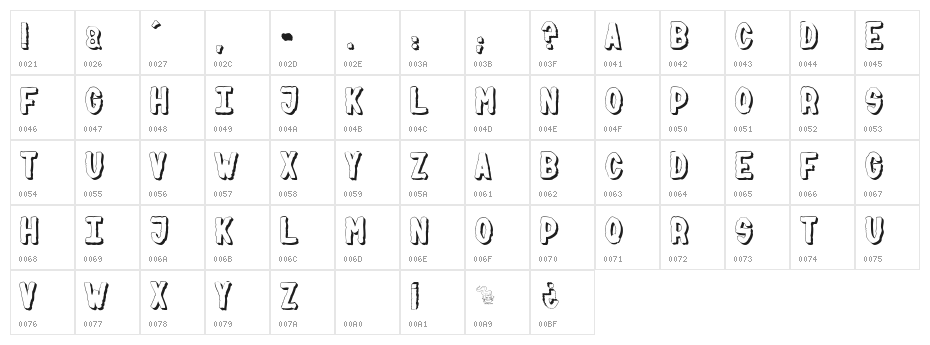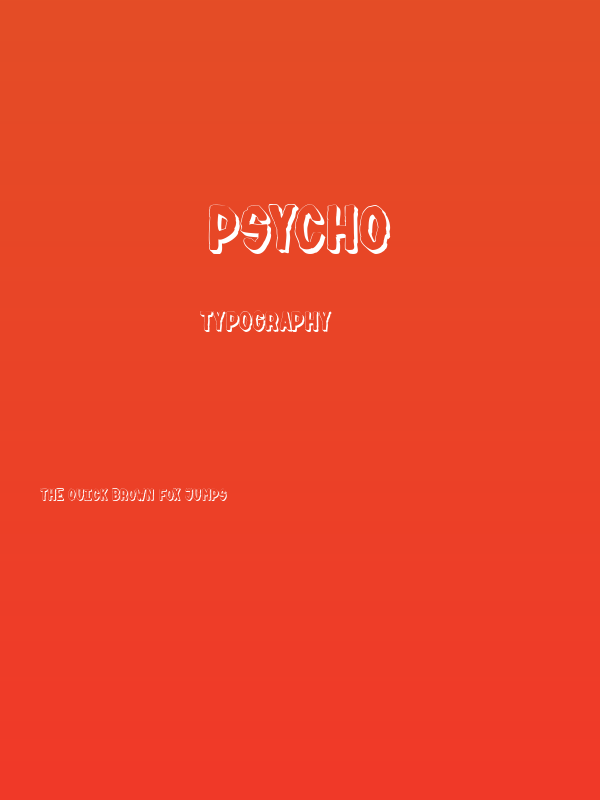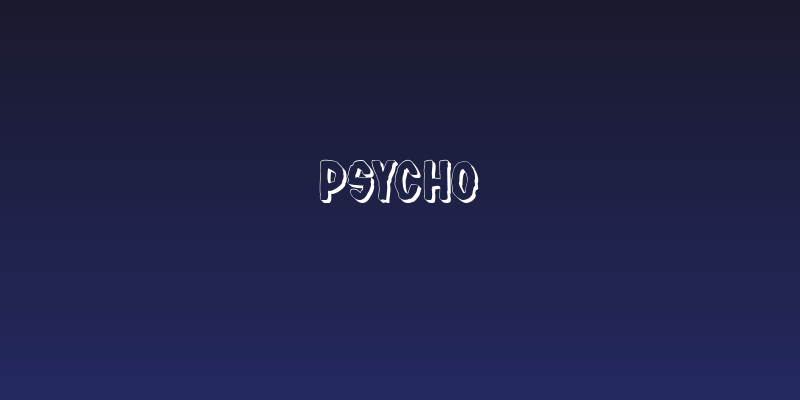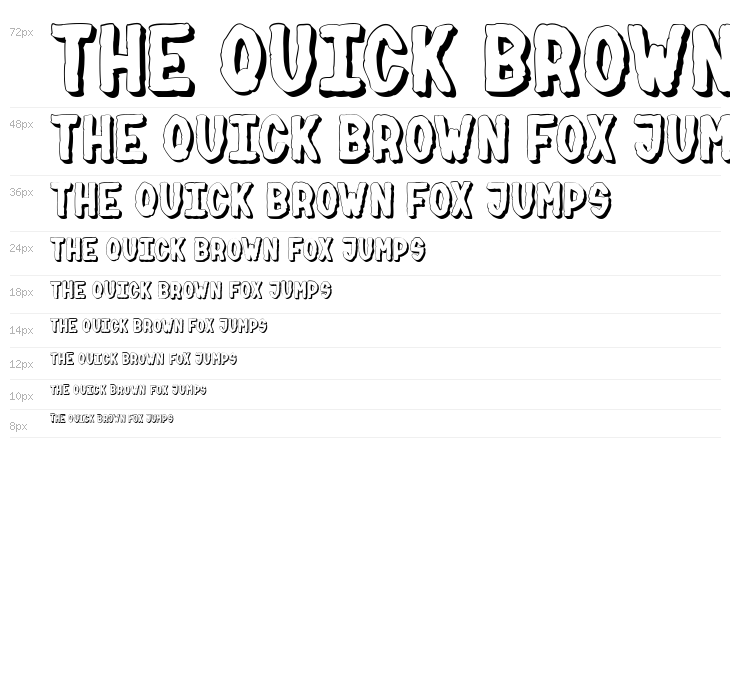
PSYCHO Font
✎ Gothic
| 分类 | Gothic |
| 整体风格 | Playful, Cartoonish |
| 使用场景 | Headlines, Posters, Logos |
| 推荐项目 | Ideal for children's book covers, comic strips, playful posters, and party invitations. |